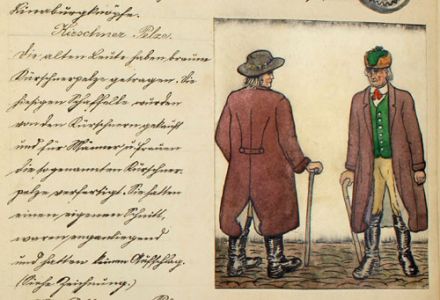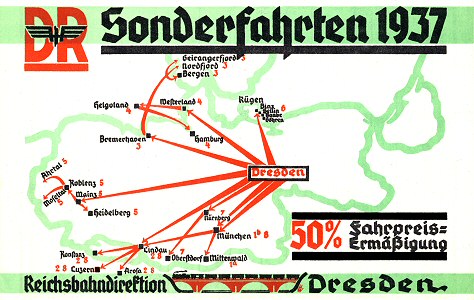
Schaftstiefelgrotesk?
Bei der Jessen-Schrift war das Ziel eine ausgesprochene Bibel-Schrift zu schaffen, die hieß ja auch während der Entstehungszeit Bibel-Schrift.
Diese wurde ja auch nie als Schaftstiefelgrotesk bezeichnet.
Also, die "National" kann ich überhaupt nicht gut lesen, da flimmert's so, dass mir die Augen wehtun. Das Gleiche gilt für "Kraft durch Freude" ...1400_b50f3749a1a911c321f681ed3ee34d65_1.jpg
... Das Gleiche gilt für "Kraft durch Freude"
da stimm ich dir zu.
trotzdem finde ich die national lesbarer als eine schwabacher.
Ich glaube, das ist reine Gewohnheit.
Aus heutiger Sicht müßte doch eigentlich eine Schrift wie die Element leicht und gut lesbar sein, kommt sie doch viel näher an die Grotesken heran.
Nö. Schwabacher geht besser, zumal für mich.
Aber es gibt auch schöne Ferienplakate (off topic, sozusagen):
... Das Gleiche gilt für "Kraft durch Freude"
da stimm ich dir zu.
trotzdem finde ich die national lesbarer als eine schwabacher.
Ich glaube, das ist reine Gewohnheit.
Aus heutiger Sicht müßte doch eigentlich eine Schrift wie die Element leicht und gut lesbar sein, kommt sie doch viel näher an die Grotesken heran.
Das seh ich auch so. Nach dem ich einige Zeit viel ganze Bücher in gebrochenen Schriften gelesen hab, habe ich keine schwierigkeiten damit.
Sagt mal, beim Plakat »Reichbahn-Auskunftei für Güterverkehr« ist bei »Eisenbahn-Transporte
Aber es gibt auch schöne Ferienplakate (off topic, sozusagen):
Aber eine viel langweiligere Schrift. Die Ostsee und Ostpreußenplakaten finde ich allerdings auch sehr schön.
Florians Beispiel ist doch aus Sicht eines Lesers, der die Gebrochenen als den Standard empfindet, durchaus schlüssig. Die Grotesk wird als Auszeichnungsschrift verwendet.
Nachfolgend ein Beispiel aus dem Anfang der 20er Jahre.
Quelle:
Das Gesicht der Demokratie
Ein Bilderwerk zur Geschichte der deutschen Nachkriegszeit
Verlag von Breitkopf & Härtel, Leipzig, 1931
Mit einem Vorwort von Friedrich Georg Jünger
Bei Spiegel online gesehen:
das thema wurde bereits im fontblog mal angesprochen:
ich glaube herr heil will aufgrund seines namens etwas vorbeugen.
dies mit einem morphing von »nazi fraktur« bis hin zur »spd-schrift«
zu verbildlichen ist natürlich ein hohn, dass heißt also die npd formiert mehr und mehr zur spd?
selbst das ’spd-umbra’ beweisst dies, es ist diesmal sehr braun geworden und wenn ich mir dann noch die farbkombination der webseite anschaue …
ich glaube herr heil will aufgrund seines namens etwas vorbeugen.
Harharhar, wohl wahr. Du meine Güte! Ich dachte, dass sei ein selbst zusammengestoppeltes Plakat einer alternativen Klezmer-Band o. ä. – aber dass dies eine ›offizielle‹ Kampagne ist: peinlich…
dies mit einem morphing von »nazi fraktur« bis hin zur »spd-schrift« zu verbildlichen ist natürlich ein hohn, dass heißt also die npd formiert mehr und mehr zur spd?
Sehr treffend bemerkt!! Welch Eigentor…
Bei Spiegel online gesehen:
FlorianG
... Die Grotesk wird als Auszeichnungsschrift verwendet. ...
Die Auszeichnugsschrift ist doch die Fette Fraktur. Die Grotesk steht darunter?
Zur Überbreite bei manchen Seiten:
Bei manchen Seiten habe ich das Problem auch. Aber nicht bei allen Seiten zu einem Thema. Es scheint mei mir auch nichts mit der Länge der Links zu tun zu haben.
Ich vermute jetzt, es tritt nur dann auf,wenn jemand ein Bild mit URL einstellt,
welches über die Tabellengröße der Antwortseite herausgeht.
Auf dieser Seite ist es ja „noch“nicht, da kein solches „breites“ URL-Bild eingestellt wurde.
Ich möchte darum bitten, daß sich die Diskussion ausschließlich um die typographischen Themen dreht und nicht irgendwelche parteipolitischen, undemokratischen Äußerungen schon wieder denselben Mist auslösen, den wir gerade hinter und haben.
Alternativ diskutieren wir es aus.
Dann aber werde auch ich meinen Standpunkt nennen.
NOCH ist es typografisch. es geht um das morphing der schrift.
von fraktur zur spd-hausschrift. und darunter im punkigen-trash-
stempel-stil ein hinweis das man den nazis null toleranz gibt.
wieso macht man das plakat braun, obwohl es doch von der SPD
mit Deutsch-Kurrent als Normalschrift und unsere jetzt benutzte Latein-Antiqua als Auszeichnung.
Aus dem Gemeindegedenkbuch von Stašov (Dittersbach), Böhmen. Begonnen 1924.
...bürgknöpfe.
Kirschner Pelze.
Die alten Leute haben braune
Kürschnerpelze getragen. Die
hiesigen Schaffelle wurden
von den Kürschnern gekauft
und für Männer u. Frauen
die sogenannten Kürschner-
pelze verfertigt. Sie hatten
einen eigenen Schnitt,
waren enganliegend
und hatten keinen Aufschlag.
(siehe Zeichnung.)